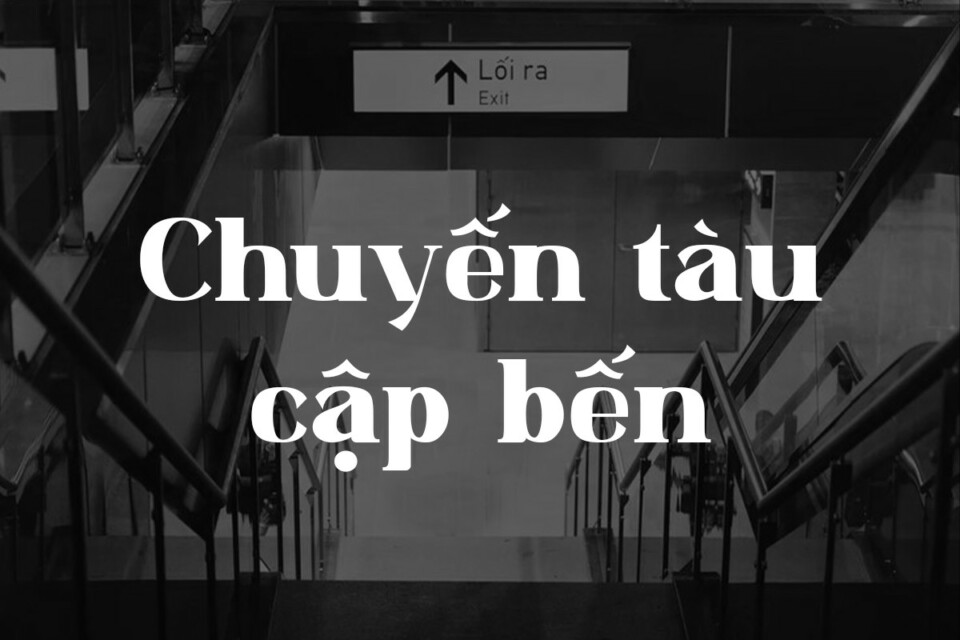
Font việt hoá MJ Megants – Bộ Font Chữ Sang Trọng Cho Thiết Kế Việt
Giới thiệu về Font việt hoá MJ Megants
Trong thế giới đồ họa hiện đại, việc lựa chọn một Font Chữ phù hợp đóng vai trò quyết định đến tính thẩm mỹ của sản phẩm. Font việt hoá MJ Megants là một trong những bộ phông chữ serif mang phong cách cổ điển xen lẫn nét hiện đại tinh tế. Với các đường nét thanh mảnh, uốn lượn nghệ thuật, bộ font này cực kỳ phù hợp cho các thiết kế yêu cầu sự sang trọng và đẳng cấp cao. Phiên bản việt hoá giúp người dùng tại Việt Nam dễ dàng ứng dụng vào các phần mềm đồ họa mà không lo lỗi hiển thị dấu câu.
Đặc điểm nổi bật của Font việt hoá MJ Megants
Thiết kế Serif tinh tế và chuyên nghiệp
Đặc trưng của MJ Megants nằm ở những nét chân chữ (serif) được gọt giũa tỉ mỉ, tạo cảm giác chuyên nghiệp và uy tín. Các ký tự được thiết kế với độ tương phản cao giữa nét thanh và nét đậm, giúp văn bản trở nên cuốn hút và dễ đọc hơn. Đây là lựa chọn lý tưởng cho các bạn học sinh, sinh viên khi thiết kế slide thuyết trình hoặc làm báo cáo dự án sáng tạo tại trường học.
Tính ứng dụng đa dạng trong thực tế
Bộ font này không chỉ giới hạn trong thiết kế logo hay bộ nhận diện thương hiệu. Bạn có thể sử dụng MJ Megants cho bìa sách, thiệp mời, tiêu đề tạp chí hoặc các bài đăng trên mạng xã hội. Sự linh hoạt của nó giúp mọi tác phẩm trở nên có hồn và mang đậm dấu ấn cá nhân của người thiết kế.
Để tận dụng tối đa vẻ đẹp của font, bạn nên kết hợp nó với các phông chữ không chân đơn giản nhằm tạo sự cân bằng cho bố cục. Việc cài đặt vô cùng nhanh chóng, chỉ cần tải về và cài đặt trực tiếp vào hệ thống máy tính. Hy vọng bộ Font Miễn Phí, Font Việt Hóa, Font việt hoá MJ Megants sẽ trở thành công cụ đắc lực giúp bạn tạo nên những sản phẩm truyền thông ấn tượng và chuyên nghiệp nhất trong tương lai.